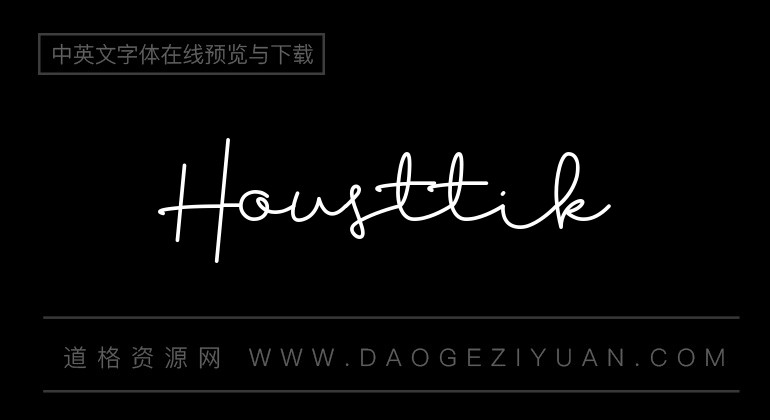
Housttik
Housttik 是一款个性化的英文字体,它具有灵活的曲线,温柔的线条,以及活泼的色彩,能够为设计师提供无限的创意空间。它的特点是层次感强,曲线优美,笔画细腻,可以让设计师制作出充满活力的设计作品。Housttik 字体可以用在海报、标志、网页、广告等多种场景中,能够营造出独特的视觉效果。
Housttik是一款非常不错的手写艺术字体,具有很好的视觉感,适合于文化类的宣传设计、商业类品牌的广告和产品包装设计以及个性化文字排版等较多场景。